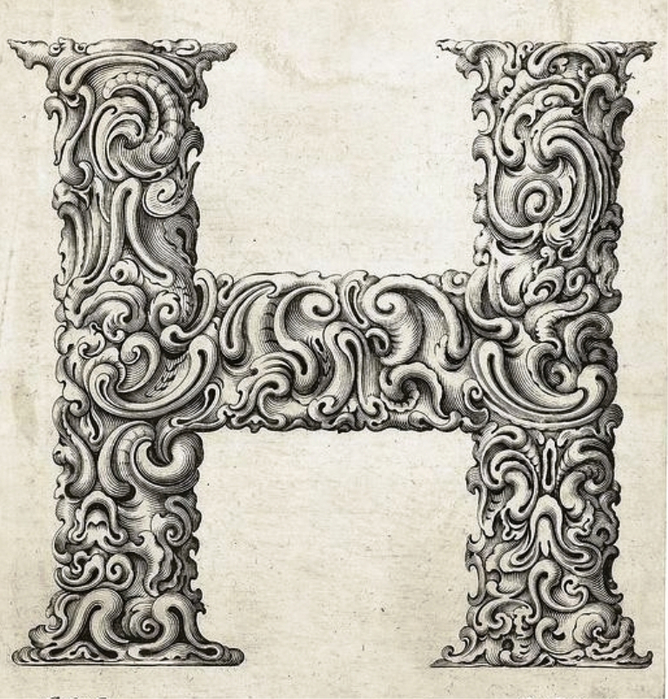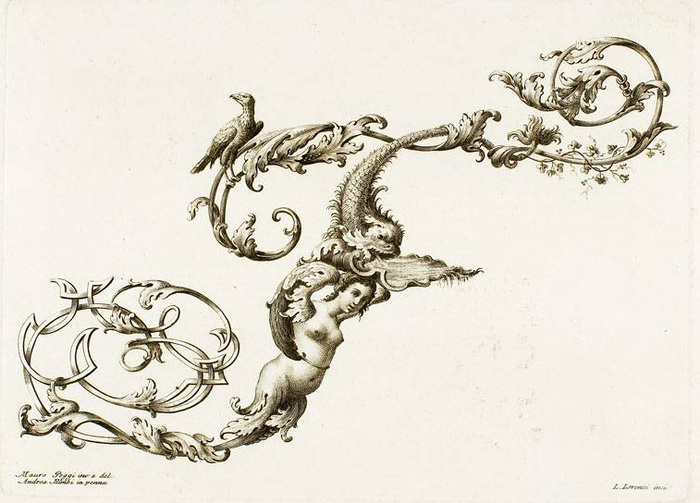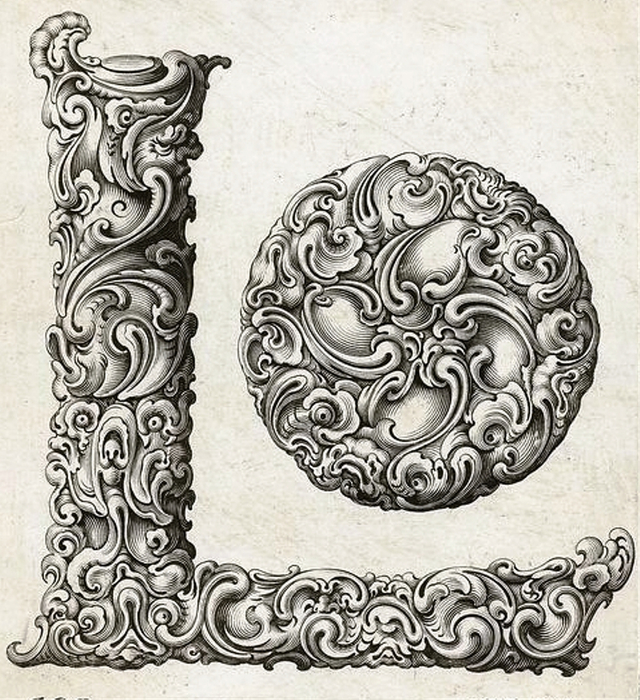
Развитие антиквенного шрифта — CraftbrotherTypes2011
Переходная антиква
Изменения и совершенствование в технике печати, а так же отливке литер служили и предпосылками для изменении стиля антиквенного шрифта. Первыми «ваятелями литер» были граверы ювелиры. Они могли вырезать на металле самый тонкий рисунок и обладали секретом отливки тончайших деталей. Говорят, что для отливки первых шрифтов использовался состав, который ювелиры использовали для подделки серебряных украшений, сплав из олова, свинца и сурьмы. Этот состав, под названием «гарт» (твердый) с небольшими изменениями дошел до середины 20 века, когда наборный шрифт окончательно перекочевал из типографий в музеи.
Граверы шрифта
были очень искусны, но печатники 15 века не могли позволить себе шрифта с
тонкими штрихами и узкими концевыми элементами. Металлический шрифт рвал
грубую, рыхлую бумагу. В рецептах типографских красок люди не достигли
совершенства. В качестве красителя использовались перетертые, пережженные
косточки винограда (знаменитая краска «кость жженая»), связующим веществом был
бараний жир.
В эпоху барокко художники стремились скорее передать в шрифте характер стиля своего времени, чем следовать за рукой каллиграфа. Бумага и краски стали совершеннее. Новый стиль, богатый вычурными орнаментами требовал от типографов соответствующего оформления книг. В первую очередь это коснулось оформления титулов, буквиц, виньеток. Но в графике самого наборного шрифта также произошли изменения.
Прежде всего
изменился контраст штрихов. Соединительные линии стали тоньше. Концевые
элементы букв и засечки (серифы) больше не имитировали росчерк пера, их форма
скорее копировала завитки барочных орнаментов. В довершении торжества стиля в
некоторых буквах появились декоративные каплеобразные элементы. Например, в
строчных буквах «а», «j» «r».
Для нас такая форма кажется привычной, но подобные элементы декора в антикве ренессанса отсутствовали, сравните с аналогичными знаками в гарнитуре
Лазурского.
Антиква переходного стиля во Франции
Изменился не только стиль шрифта, но и отношение его значению в масштабах государства. Правители понимали, что печатное слово может оказывать сильное воздействие на умы сограждан. Если раньше шрифтом занимались энтузиасты одиночки, то в начале 18 века во Франции создание нового шрифта становится делом государственной важности.
Французский король Луи IV поручает разработать новый шрифт французской академии наук. Для этих целей была организована целая комиссия во главе с аббатом Николя Жожеоном (Nicolas Jaujeon). К проекту шрифта был применен научный метод. Шрифт строился по сетке 8х8 квадратов, каждый из которых был поделен на 6 частей. Итого 6 х 8 = 48 point (точек). Сторона квадрата была равна старому французскому дюйму. Соотношение толщины основного и дополнительного штриха строго лимитировалось 1/3. Новый шрифт назвали Роман дю Руа.
Система построения шрифта Роман Дю Руа заложила основу
типографской системе мер, в которой основной единицей измерения является
квадрат, а высота шрифта (кегель) измеряется в пунктах (от французского point,
точка).
Позже эта система была принята и доработана в словолитне Симона Фурнье
и в таком виде просуществовала до наших дней. Старые типографские наборщики
измеряли формат в «квадратах», квадрат равен 48 пунктам. Размер шрифта мы до
сих пор измеряем в пунктах (правда не в европейских, а англо-американских, но
это не пеняет сути типометрической системы).
В рисунке нового королевского шрифта была любопытная деталь. Строчная буква «l» имела совершенно лишний сериф, расположенный по верхней линии строчных букв. По замыслу авторов, по этому серифу все должны отличать королевский шрифт от прочих.
Выполнять проект по чертежам Академии наук поручили опытному
граверу Филиппу Гранджану. Работая над проектом академии, он собственноручно
награвировал 9236 литер с 1693 по 1714 г. Первая книга была отпечатана в 1702 году.
Обладая большим опытом гравера, Гранджан скептически отнесся к проекту. По
собственному усмотрению он внес в рисунок литер значительное количество
«зрительных поправок». Только благодаря усилиям и опыту Гранджана проект
состоялся.
В 1904 году директор национальной типографии в Париже Артюр Кристиан и гравер Жюль Хенаф (Jules Henaff) реализовали проект в точности. Шрифт получился очень странный, широкий, с нарочито симметричными элементами. Простая арифметика и модульная сетка не могут подменить таланта проектировщика шрифта.
Но система заложенная в основу проекта Роман Дю Руа не пропала даром. Модульная система в размере шрифтовых литер была внедрена в словолитне французского печатника Симона Фурнье. Основной единицей измерения стал «квадрат» равный 48 пунктам. Шрифты стали отливать не произвольной высоты, а строго по заданным размерам. Это позволило типографам обмениваться шрифтами произведенными в разных словолитнях. В таком виде типометрическая система виде до наших дней. Старые типографские наборщики измеряли формат в «квадратах». Размер шрифта мы до сих пор измеряем в пунктах, правда не в европейских, а англо-американских, но это не пеняет сути типометрической системы.
Фурнье издал первый учебник по типографике, который являлся в
Джон Баскервиль оказал глубокое влияние на развитие современных шрифтов. Его шрифтами очень восхищался Бенджамин Франклин, который фактически вернул их в Соединенные Штаты (которые на тот момент были недавно созданной республикой) и использовал их для публикации большинства федеральных документов. Разговор о наследстве.